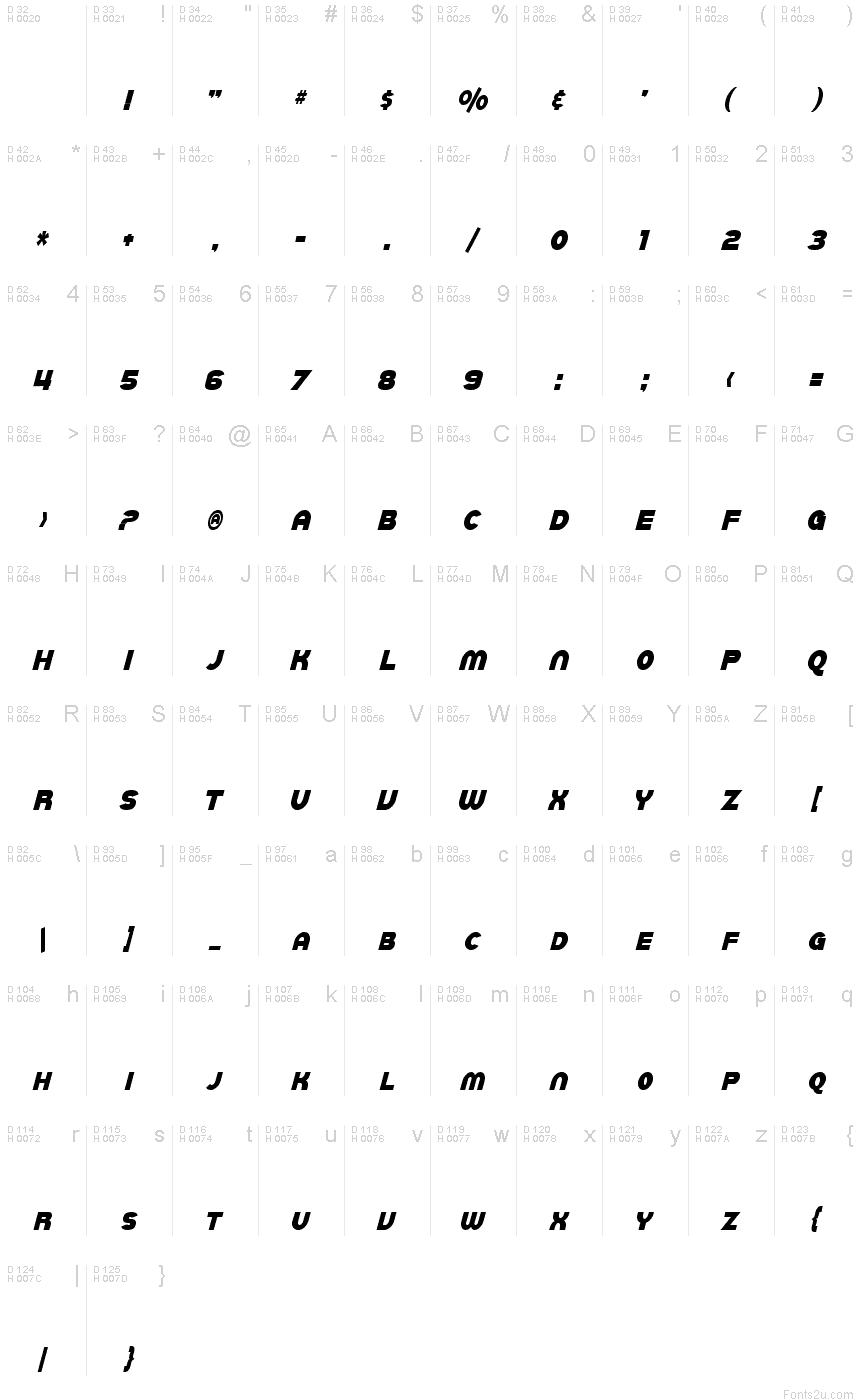
SF Juggernaut Condensed Italic od ShyFoundry to bezpłatny, pochylony i skondensowany krój typu display, emanujący nowoczesną energią. Litery nachylają się w jedną stronę w solidnym, ciągłym ruchu, łącząc masywne, ciężkie kształty z zaokrąglonymi cięciami, dzięki czemu cały alfabet sprawia wrażenie szybkiego, ciasnego i nieco agresywnego.
Ten dynamizm sprawia, że jest to naturalny wybór do brandingu sportowego, opakowań gier, plakatów akcji, okładek i plansz tytułowych, gdzie słowa muszą mieć prawdziwą siłę przebicia. Jako darmowy font, świetnie sprawdzi się również w monogramach, znakach drużynowych i krótkich nagłówkach, szczególnie gdy chcesz, by skondensowany, kursywny rytm wykonał większość pracy.
SF Juggernaut Condensed